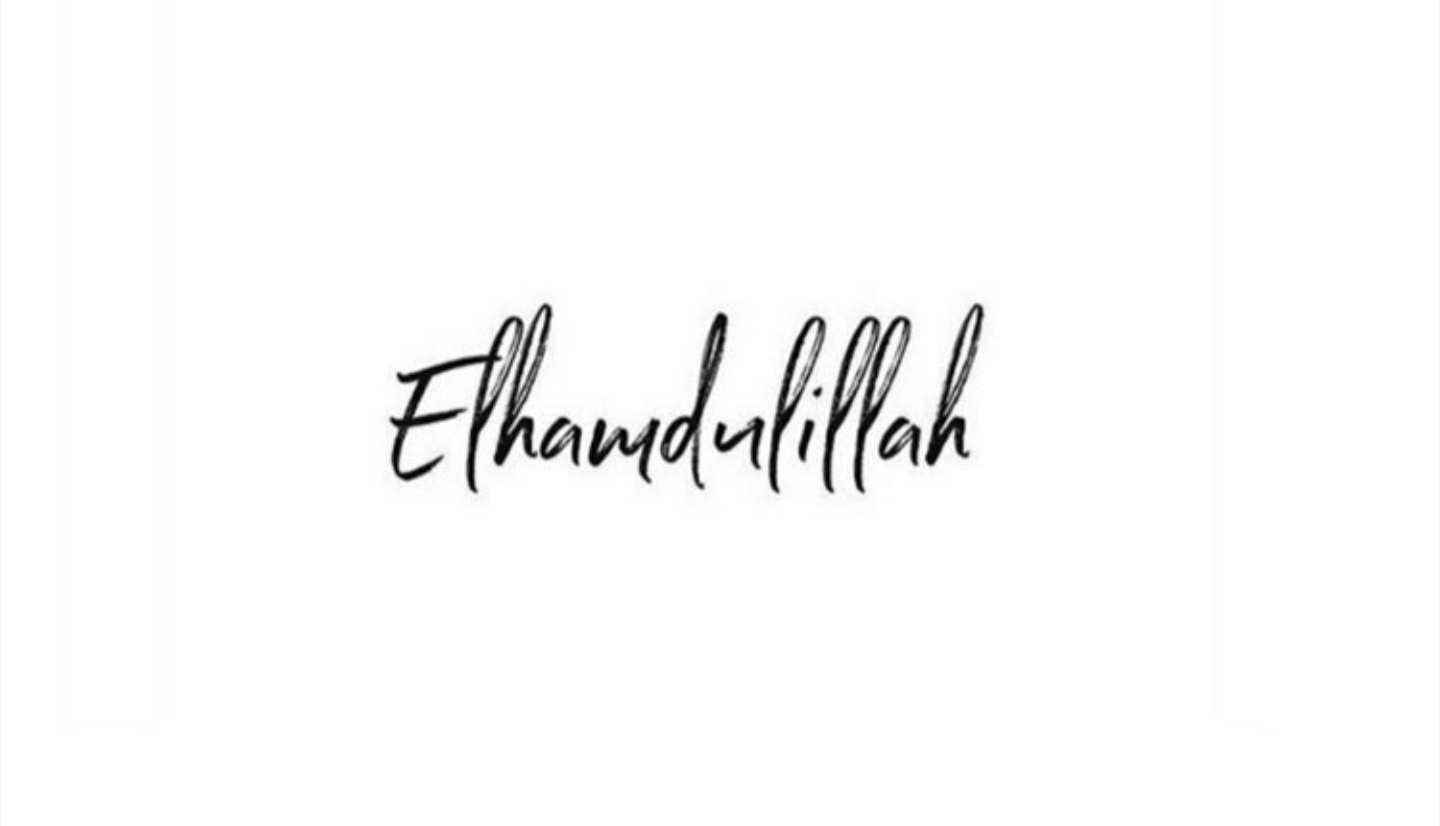
Bu font nedir? Yoksa El yazısı mı?
Arkadaşlar bu font mu? Font ise ismi nedir nereden bulabilirim?
El yazısı mı? Onu da çözemedim, siz ne düşünüyorsunuz?
Evet font gibi duruyor, "a" ve "l"harfleri birbirleriyle aynı, el yazısı ile bu kadar kusursuz birebir aynı olmazdı.
Fontun ismi " Northwell Alt Regular otf (400) " hocam.